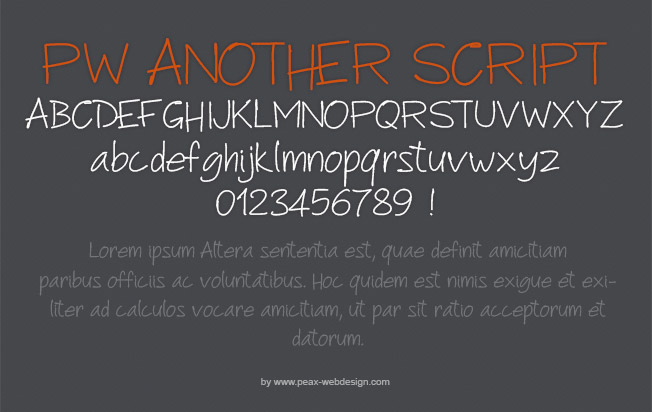
PW Another Script est effectivement une autre police manuscrite de plus : elle se différencie cependant par ses petits détails, comme le début des lettres qui présente une épaisseur plus grande. Cette police est livrée avec les caractères accentués, et vous changera du Comic Sans !